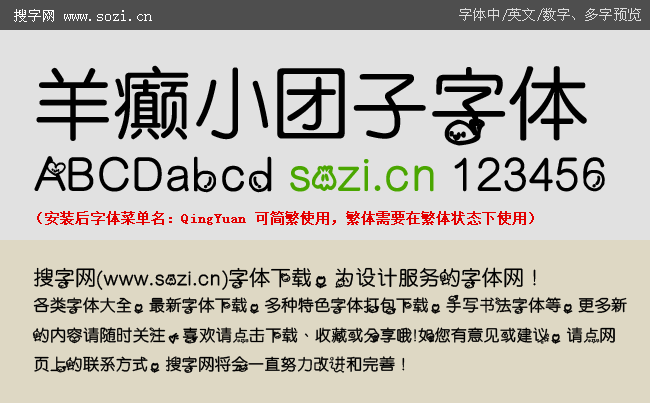
羊癲小團(tuán)子字體
搜字網(wǎng)給大家提供一款羊癲小團(tuán)子字體手機(jī)中文字體下載。這款手機(jī)字體是以圓體字體為原形,筆畫間嵌入了可愛的卡通圖案。在具備圓字體清晰端正的風(fēng)格同時(shí),卡通味也特別濃,是一款非常可愛的卡通字體,特別適合喜歡手機(jī)字體個(gè)性一些的朋友在手機(jī)上安裝使用。